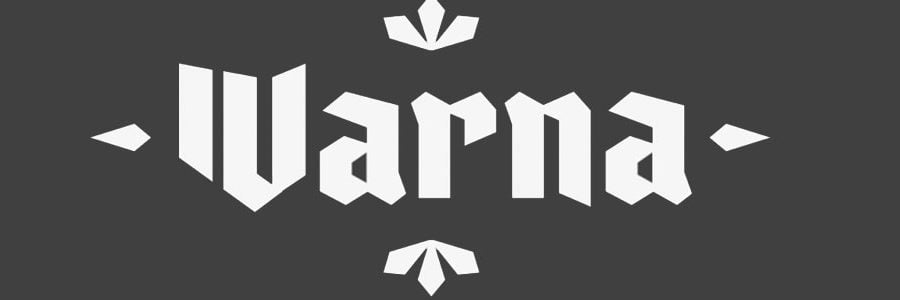
VARNA : Typographie gratuite
Varna est une police de caractères de type blackletter moderne inspirée par le designer / artiste Viktor Antonov, dont le style de signature, est une fusion de classique, moderne, rustique et high-tech.
varna typographieIl est plus célèbre pour sa direction artistique dans des jeux comme Half-Life 2 et Dishonored. Au travers de cette typo nous imaginons ce à quoi ressemblerait la «blackletter futuriste» dans l’un de ses mondes.
Viktor est originaire de Bulgarie et l’une de ses villes est Varna. Par hasard, le mot en lituanien signifie aussi « corbeau » ce qui convient bien  à une blackletter.